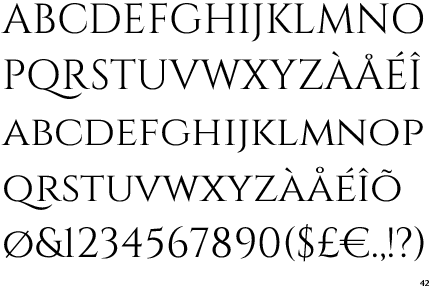
Image der Cinzel
Ich fange gerade erst an mich intensiver mit Typografie auseinanderzusetzen und habe nun aber einen Auftrag für eine Firma ein Logo zu entwerfen. Es soll sehr exklusiv und edel wirken.
Ich habe viele Schriften durchgesehen aber bis jetzt gefiel mir doch am besten die Cinzel. Dies ist aber nun eine kostenlose Schrift.
Nun wollte ich mal bei euch nachfragen wie denn das Image dieser Schrift ist.
Und ob es billig wirken würde sie zu verwenden, da sie ja auch noch kostenlos ist..
Exklusivität kommt durch die eingeschränkte Nutzung. Mir war vor Deinem Post nicht mal bewusst, dass es eine Schrift dieses Namens gibt. Da sie aber von jedem jederzeit frei genutzt werden kann, ist sie nicht exklusiv. Dies wird für gewöhnlich durch den Preis erreicht. Hatte DTL nicht eine entsprechende Politik?
Aber ein paar zusätzliche Angaben zur Zielgruppe und Branche könnten uns hier durchaus behilflich sein ;)
Wie Phoibos schon angedeutet hat, ist die Frage, was Du unter »Exklusivität« verstehst. Wenn es dabei nur um eine formal edle Anmutung geht, kann man mit dieser Schrift sicher schon die gewünschte Wirkung erreichen. Wenn »exklusiv« aber bedeuten soll, ein möglichst einzigartiges Erscheinungsbild zu kreieren, sprechen zwei Dinge dagegen:
1. Es ist ein kostenloser Font und die Wahrscheinlichkeit, dass er auch von vielen anderen genutzt werden könnte ist vergleichsweise hoch.
2. Dieser Schrifttyp (Trajan und Co.) wird sehr sehr häufig eingesetzt. Gefühlt ist er auf jedem dritten Filmplakat, jedem vierten Buchtitel und jedem fünften CD-Cover zu sehen.
Ja sorry, natürlich hätte ich die Schrift mit posten sollen.
Ich dachte, dass sie eine bekanntere Schrift ist, da sie mir schon öfters begegnet ist.
Also das Logo ist für eine Immobilenmaklerfirma die mit sehr teuren Immobilien handelt.
Daher sollte das Logo edel und nach "viel Geld" aussehen. Ist natürlich absurd, dann auf eine kostenlose Schrift zurückzugreifen, aber bis jetzt hat sie mir einfach am besten gefallen...
Ja hab ich mir schon fast gedacht.. Wenn sie so oft eingesetzt wird suche ich doch lieber nach einer anderen.
Danke für die Links. Gefallen mir sehr gut, besonders die Zweite. Aber leider gibt es davon keine bold-Version.. und mein Logo braucht einen etwas kräftigere Schnitt.
Ist alles traianeske nicht völlig ausgelutscht? Da könnte man ja auch gleich eine Garamond nehmen. Wie wäre es mit der Überschrift? Die ist so neu, dass sie noch exklusiv wirkt ;)
Aber die "Überschrift" ,finde ich, passt nicht so gut zu der Immobilenfirma. Dazu ist sie zu grazil. Sie passt für mich eher zu Mode und Fashion.
nur weil ein font ein freefont ist muss er nicht billig wirken, deine gestaltung hat da auch einen gewissen einfluss.
bsp.: ein filmplakat in cinzel sieht bestimmt besser aus als in der (kostenpflichtigen) trajan, die einfach zu oft verwendet wurde. die cinzel ist zwar kostenlos aber noch lange nicht so weit verbreitet wie eine comic sans oder ähnliches.
für eine immobilienfirma kann ich mir das zwar gerade nicht so vorstellen, kommt aber sicherlich auch auf deine umsetzung an. ich hab da eher etwas schmales, hohes im kopf. ähnlich corvinus:
ja, aber das ist ja auch alles trajan und co. :-?
etwas edles und luxus wird auch gern mit dieser art von schriften verbunden:
siehe modelabels wie chanel oder uhrenhersteller.
hauptsache keine bank gothic oder copperplate, die wirken durch ihre massive verwendung eher billig.
Ich wollte auch gerade schreiben, dass filigrane Versalien mit ausgeprägten Serifen für Makler von (angeblichen) Luxusgrundstücken sehr abgenudelt sind. Wenn es für Laien auf den ersten Blick gleich unbedingt eindeutig edel-elegant aussehen muss, wie wär’s mit einer eleganten Schreibschrift? Da sind in Norberts Sammlung zwar auch einige dabei, aber m.E. sind sie bei weitem nicht so weit verbreitet wie die trajanschen. Man könnte vielleicht bei den klassischen Spencerian scripts beginnen (die PF Champion ist z.B. schön und teuer) und von denen ausgehend so weit exotischer abweichen wie es der Kunde zulässt.
Ansonsten bin ich auch sehr auf der "Thema" (http://www.typonine.com/fonts/font-library/thema/) hängengeblieben und würde diese am liebsten nutzen. Nur würde ich sehr gerne eine kleine Swashform auf einen Buchstaben legen und weiß nicht ob es erlaubt ist.. Ich verstehe die Lizenz leider nicht richtig.. Mein Englisch ist grauenvoll..